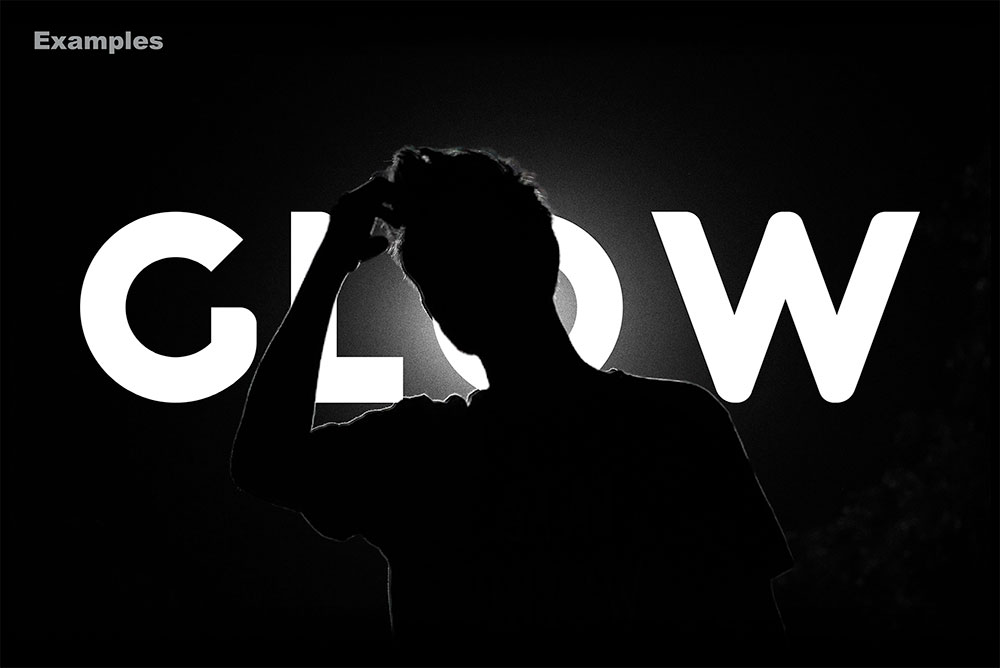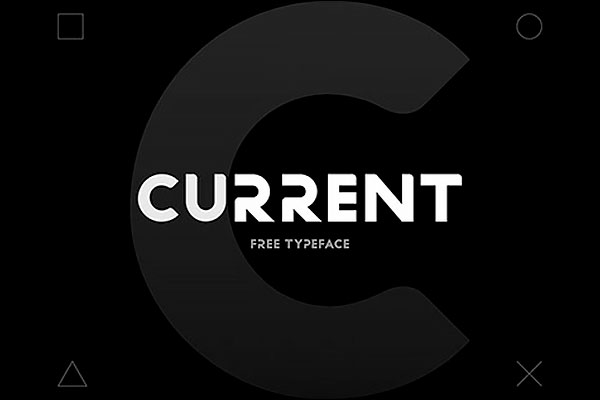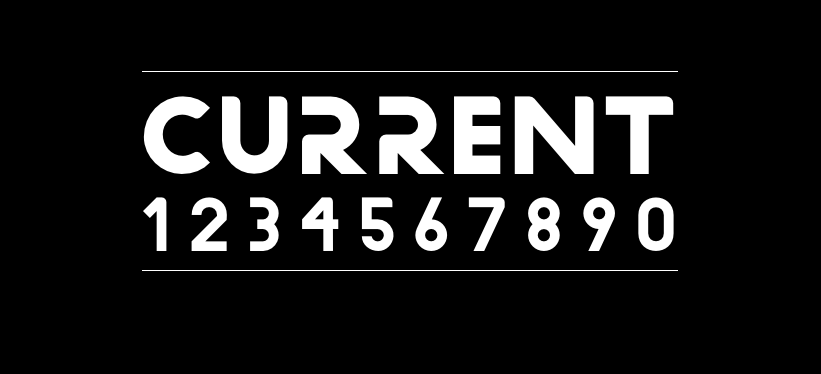
字体下载 CURRENT
CURRENT
CURRENT 是由Matt Pendrill设计和开发的大字体,大胆而美丽的无衬线字体。凭借其简洁的线条,圆角和醒目的外观,它体现出了其同类字体中不常出现的力量和力量感。因此,它可以很好地用作广告牌,海报,网站等的标题。最重要的是,它对于个人和商业用途都是免费的!